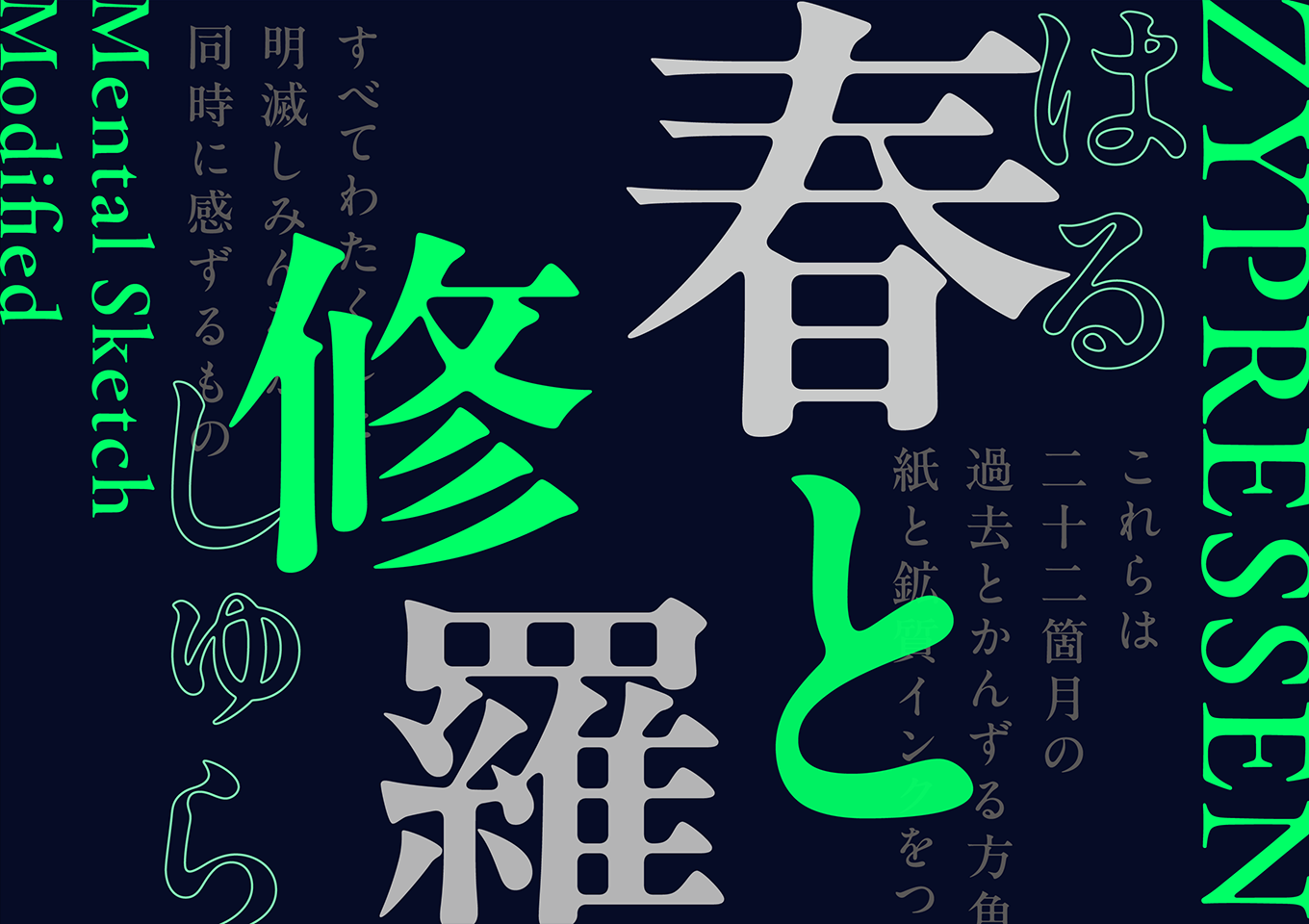
「A1明朝(AP版)」は、モリサワ最初期から長く愛されているオールドスタイルの明朝体です。漢字のゆったりとしたカーブと、かなの優美な表情が生み出す独特の味わいが特徴です。画線の交差部分に写植特有の墨だまりを再現し、やわらかな印象と自然な温かみを感じさせます。AP版では従来の1ウエイトから3ウエイト(R/M/B)に拡張し、また欧文も16世紀のフランスにルーツをもつローマン体に着想を得たクラシカルなデザインにリニューアルしました。